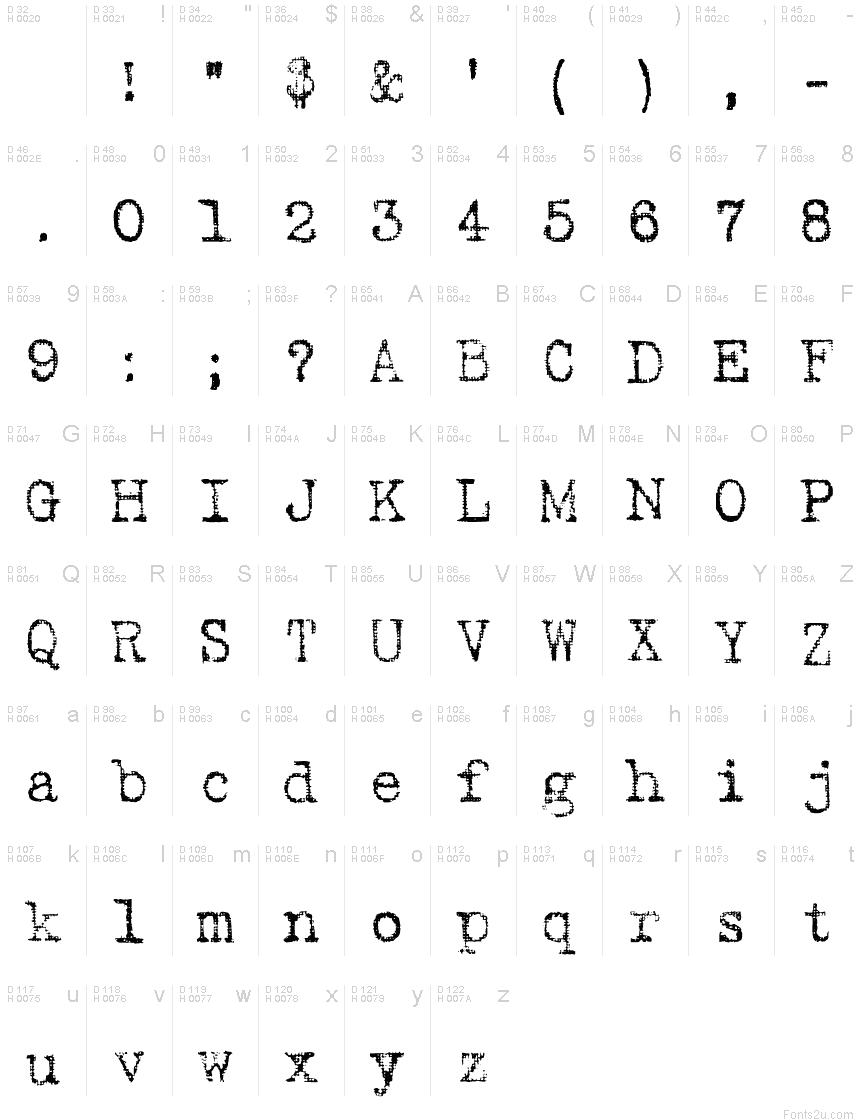
Fucked Olympia to imponujący i przyciągający wzrok krój typu display, emanujący surową, spatynowaną estetyką. Zaprojektowany przez duet J.B. Thyssen i H. Zimmerman, ten font natychmiast przykuwa uwagę swoim zniszczonym, erodowanym wyglądem. Nieregularne, poszarpane kształty liter i różnice w grubości linii nadają mu szorstki, industrialny urok. Sprawia to, że idealnie nadaje się do odważnych nagłówków, okładek albumów i wszelkich projektów, w których pożądana jest wyrazista, surowa obecność. Jego wszechstronny styl płynnie łączy się zarówno z nowoczesnym klimatem miejskim, jak i z projektami w stylu retro.
Bezkompromisowy charakter i niekonwencjonalny urok tego kroju pisma sprawiają, że jest to atrakcyjny wybór dla projektantów, którzy chcą wyraźnie zaznaczyć swoją obecność.